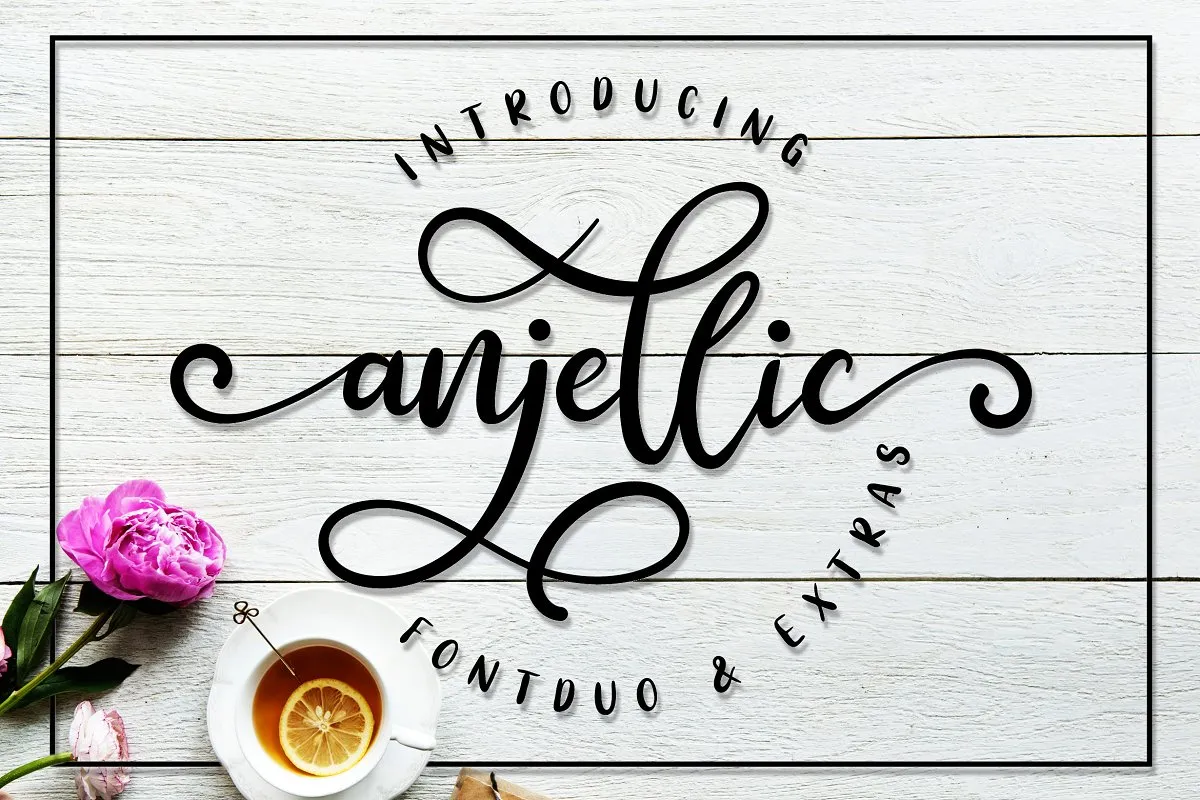
Anjellic Script Font – Download Grátis
Anjellic Script Font é uma excelente opção para designers que procuram estilos únicos para seus trabalhos visuais. Se você está à procura de uma fonte com traços fluidos e elegantes, esta deve ser a escolha perfeita. Com sua estrutura moderna e harmoniosa, Anjellic oferece um equilíbrio perfeito entre script e sans-serif, permitindo que designers usem essa combinação em vários projetos de design. Seja para criar uma identidade de marca única, personalizar postagens nas redes sociais ou desenvolver lindas capa para revistas, Anjellic é ideal. Esta fonte oferece um tom suave e harmonioso que se adapta perfeitamente às necessidades do designer. O Anjellic Script Font é uma escolha inteligente não apenas para designers de moda, mas também para aqueles que procuram um estilo elegante para seus projetos digitais e impressos.